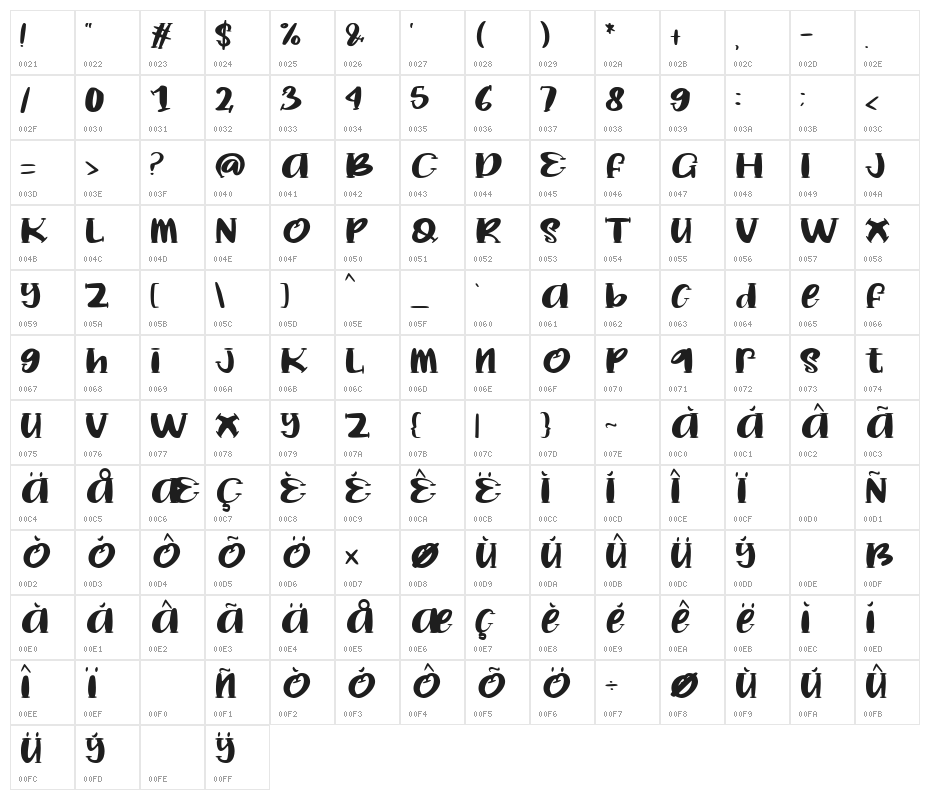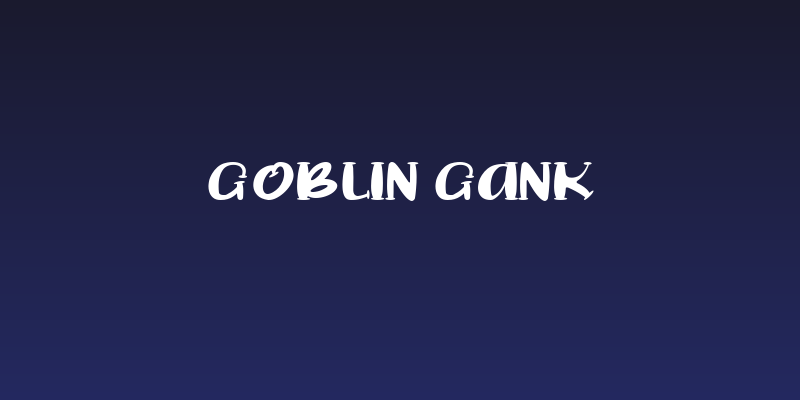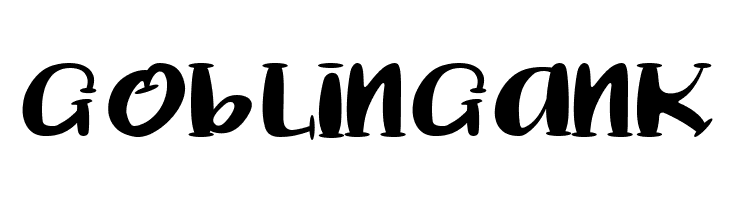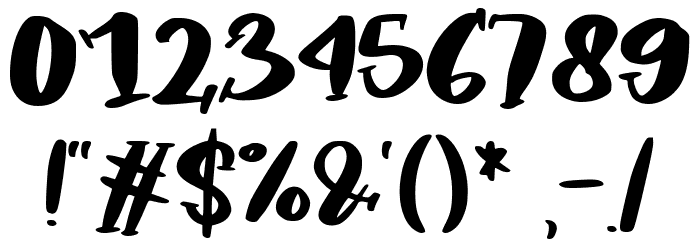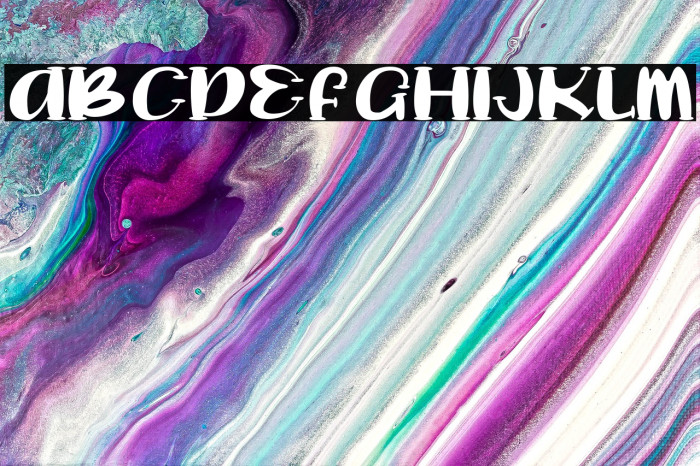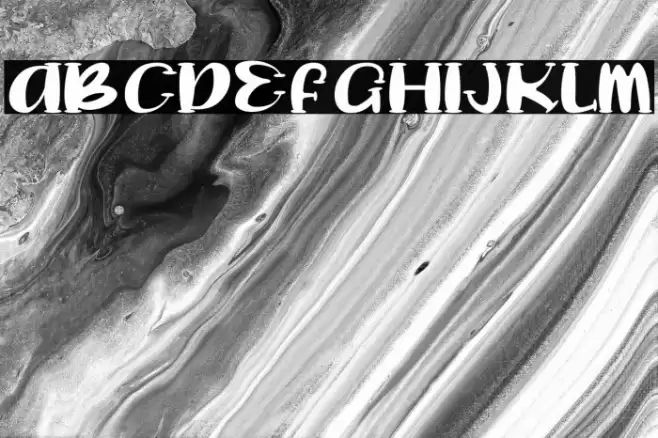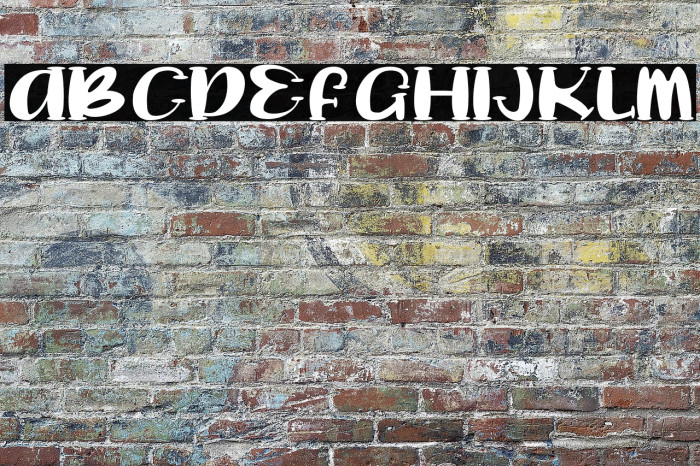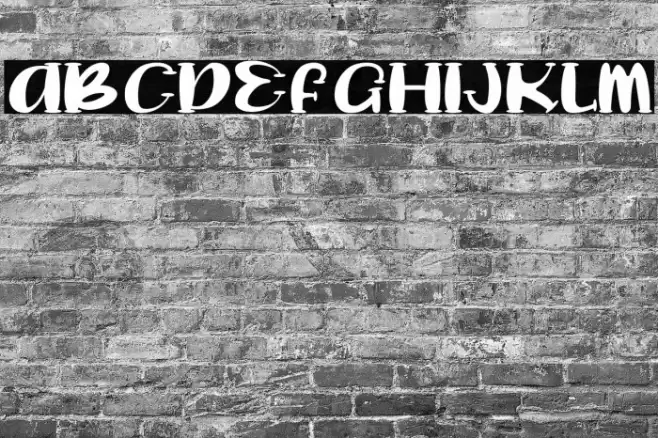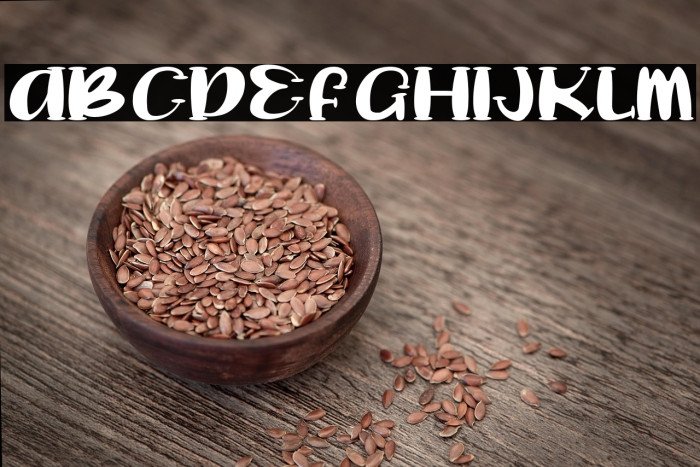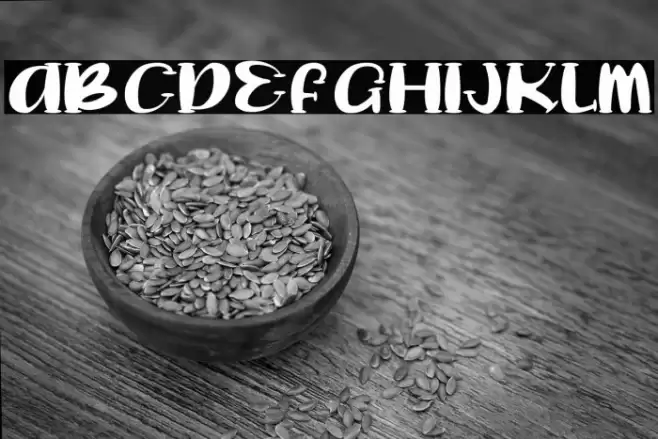
Goblin Gank Font
| Stil general | Playful, Whimsical |
| Caz de utilizare | Headlines, Posters, Branding |
| Proiecte propuse | Ideal for children's book covers, playful branding, event posters, and creative social media graphics. |